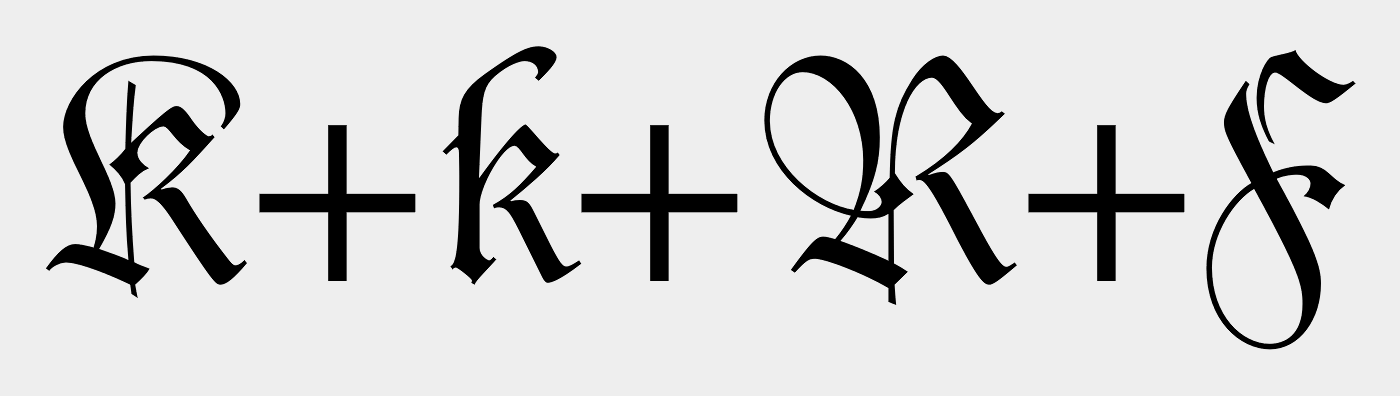
"Antiquaisierte" Fraktur - Gibt's das?
Das stimmt natürlich, es wäre dann keine besonders leserfreundliche Schrift. Allenfalls für den Display-Einsatz geeignet.
Aber das Beispiel der Andron zeigt, wie ich finde, ganz gut, dass man mit ein bisschen Anpassung die Buchstaben auch eindeutig und lesbar hinbekommt.
@j4y: Ja, ganz genau so hab ich mir das vorgestellt, Vielen Dank! Jetzt kann man natürlich hergehen und je nach der Fraktur, die man betrachtet, auch ein großes R als Grundlage nehmen, weil der kleine obere Balken des k in manchen Frakturschriften ja auch einen Bogen schlägt und sich wieder mit dem Stamm verbindet. - Es gäbe unzählige Möglichkeiten!
ich hätte da auch eher einen Bogen gezeichnet statt des Winkels – allerdings, ohne dass er sich mit dem Rest verbindet, damit es eben nicht zum R wird.
Jetzt kann man natürlich hergehen und je nach der Fraktur, die man betrachtet, auch ein großes R als Grundlage nehmen, weil der kleine obere Balken des k in manchen Frakturschriften ja auch einen Bogen schlägt und sich wieder mit dem Stamm verbindet.
Beim ersten Hinschauen war ich mir nicht sicher, ob das ein F, ein K oder ein R sein soll.
Ich hatte bewusst die Bogenform vermieden, obwohl sie üblicher ist, um das K besser vom R zu unterscheiden. Wenn dieses K nun auch noch mit dem F verwechselt wird, sollte ich mir wohl nochmal Gedanken machen. Danke auch an Schnitzel für die Anregung. (Ein K ähnlich wie in der Duc de Berry könnte ich mir für die Kursive vorstellen.)
Hermann Zapf hat zu dieser Fragestellung schon vor vielen Jahren sehr deutlich Stellung bezogen: [...]
Ich glaube Albert Kapr hat sich in seinem Frakturbuch ähnlich geäußert. Dass Leute, die unendlich viel mehr als ich von Schrift verstehen, so denken, gibt mir schon zu denken. Andererseits finde ich es schade, dass Antiqua und Fraktur als unversöhnliche Gegensätze gesehen werde, von denen die eine die andere zwangsläufig ablösen musste. Wenn ich drüber nachdenke, Fraktur und Antiqua stilistisch anzugleichen, frage ich mich auch, ob man sie nicht in einem Schriftsystem vereinen kann.
Andreas Stötzner hat vor einiger Zeit ein trikamerales Alphabet, bestehend aus Majuskel, Mediuskel und Minuskel, ins Spiel gebracht. Ich finde diese Idee sehr interessant.
Ich glaube, das Problem ist weniger, dass die Fraktur irgendwie die Leserlichkeit behindern würde, wie manchmal behauptet wird (ist alles eine Sache der Gewöhnung), sondern dass sie unwiederbringlich mit dem Dritten Reich assoziiert wird. Im besten Falle wirkt sie auf viele einfach antiquiert. Wir hatten letzthin ein Projekt (ich studiere Industriedesign) über Keramik; eine Gruppe hatte sich auf im Dunkeln leuchtendes Porzellan spezialisiert und dafür eine schwarz angestrichene Kiste gebaut. Über dem Guckloch haben sie in Stenciltechnik den weißen Fraktur-Schriftzug: "Schau nei!" (Ja, wir kommen aus Bayern!) angebracht. Das war jetzt noch nicht mal so eine typische "Nazi-Fraktur", wie man sie von Propagandaplakaten her kennt, sondern eine recht harmlose Breitkopf-Fraktur (Wenn ich mich nicht täusche). Und trotzdem war bei vielen schon die Assoziation klar und es wurden dann auch dementsprechende Anspielungen gefrotzelt ...
Ich finde es daher immer begrüßenswert, dass sich jetzt viele Gestalter der gebrochenen Schriften annehmen und mit ihren Interpretationen auf die charmanten Aspekte und Qualitäten hinweisen, z.B. wie bei der schon genannten Ode.
Die Zeit allerdings, in der Frakturschriften ernsthaft und mit dem Ziel einer "normalen" typografischen Gestaltung entworfen wurden (und eben nicht nur für Displays, von extravagant bis ironisch), scheinen jedoch vorbei zu sein.
Naja, Antiqua und Fraktur gehören ja im Prinzip schon einer Schriftfamilie an. Aber ich denke, du meinst dann wohl eben so ein System wie das von der Lapidaria? Die mag ich auch sehr gern, sie wäre schon ohne das trikamerale System eine sehr schöne Schrift. Stötzner war ja auch an der Andron beschäftigt, die ich anfangs genannt habe.
Das trikamerale System, das ich bei der Andron und der Lapidaria eingeführt habe, bindet die Kategorie der Unzialen als Mittelglied zwischen Majuskeln und Minuskeln ein. Das hat zunächstmal mit Fraktur nichts zu tun. Oder, nicht zwangsläufig.
Allerdings habe ich auch die Andron-2-Englisch/Deutsch realisiert, die als eindeutige Antiqua-Schnitte einige Strukturmerkmale der Fraktur aufweisen, ohne allerdings das Moment des gebrochenen Striches mitzuübernehmen.
– Finde solche ›grenzüberschreitenden‹ Versuche immer interressant.